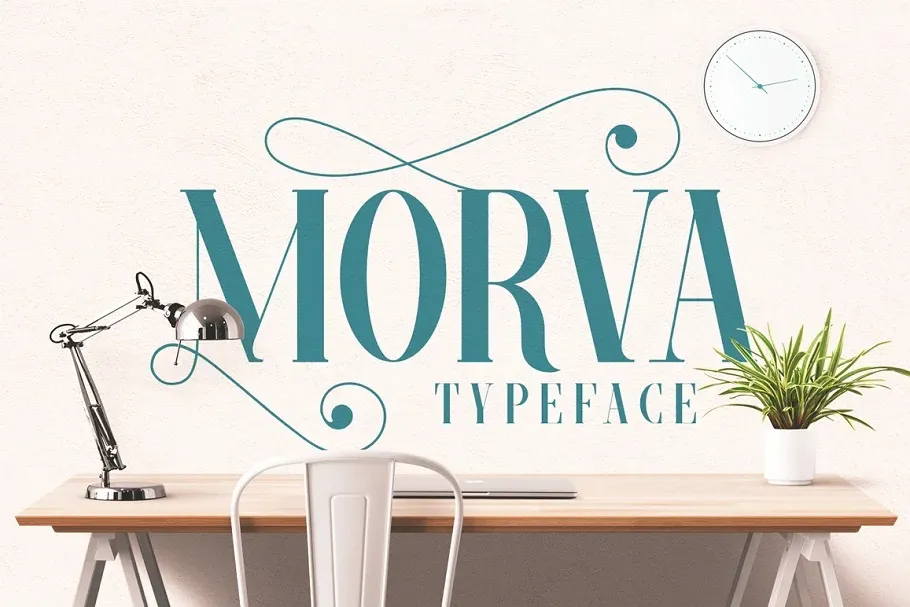
A ‘Morva Font’ é uma elegante serif que oferece alternativas estilísticas únicas, proporcionando uma beleza singular à sua designação tipo. Perfeita para criações minimalistas e simples, a Morva atende perfeitamente aos requisitos de logo moderno, cabeçalhos de website, designs de casamentos, fonts para menus de website e outros conceitos mínimos. Esta font é ideal para designers que buscam um toque sofisticado em seus projetos sem comprometer a simplicidade necessária. Compostas para uma variedade de usos gráficos, Morva torna-se uma opção conveniente para quem procura um equilíbrio entre modernidade e elegância na sua identificação visual.